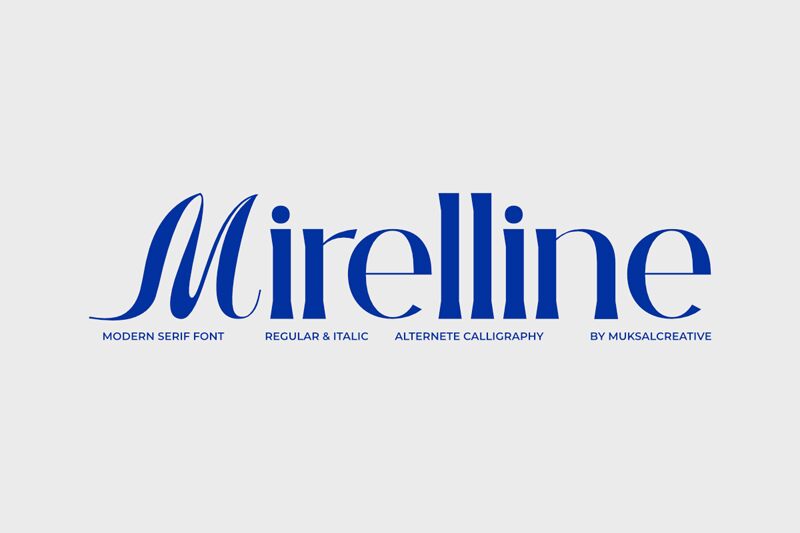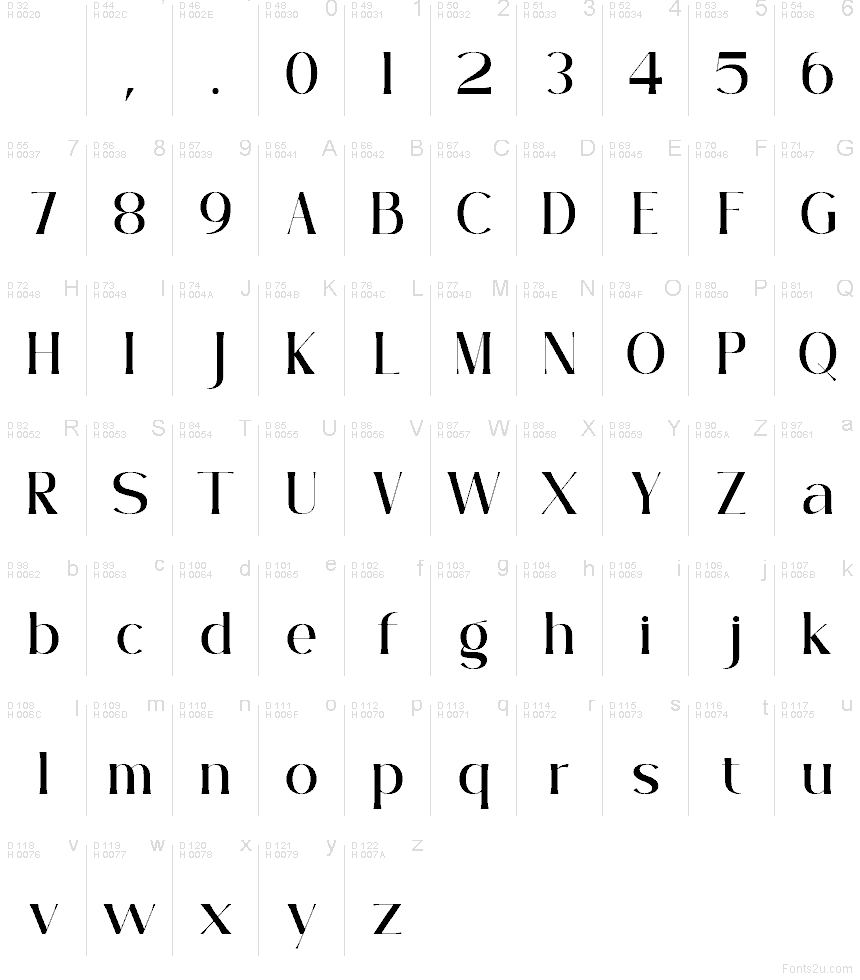
تعد Mirelline من Muksal Creative خطاً سيريفياً مجانياً عالي التباين، يتميز بأشكال عمودية طويلة ووصلات دقيقة تمنح الحروف مظهراً انسيابياً خفيفاً بدلاً من الكثافة. يتمتع تصميم الخط بأناقة تحريرية حادة، مع منحنيات طويلة وتفاصيل دقيقة تضفي على الكلمات القصيرة طابعاً راقياً يواكب عالم الأزياء.
يتناسب هذا الإيقاع تماماً مع عناوين المجلات، والهوية البصرية للمتاجر، وتغليف مستحضرات التجميل، وبطاقات الزفاف، وعناوين الكتيبات التعريفية، حيث تبرز الحاجة إلى لمسة بصرية خفيفة مع الحفاظ على القوة والرصانة. كما يضفي خط Mirelline اللمسة المثالية على قوائم المطاعم أو منشورات وسائل التواصل الاجتماعي التي تتطلب عناوين أنيقة بعيداً عن الطابع الترفيهي التقليدي.